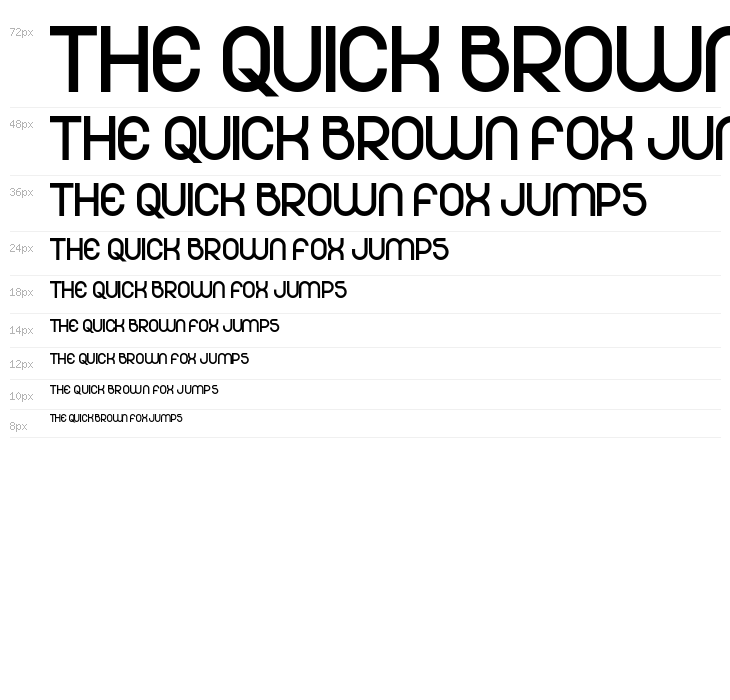
501 Font
✎ Futuristic
| Anwendungsfall | Headlines, Logos, Digital interfaces |
| Vorgeschlagene Projekte | Ideal for branding, advertising, digital interfaces, and modern editorial design. |